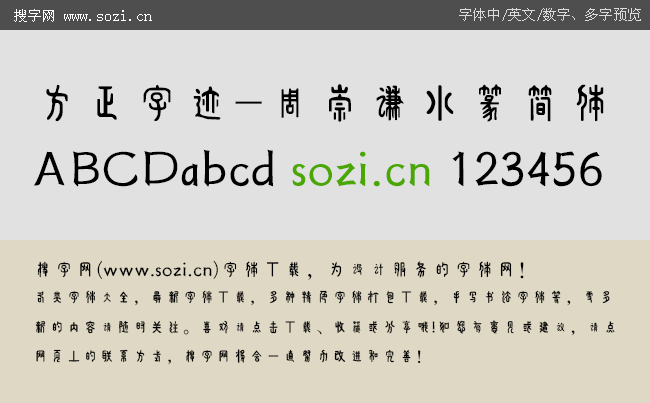
方正字跡-周崇謙小篆簡(jiǎn)體手機(jī)字體
搜字網(wǎng)給大家提供一款方正字跡-周崇謙小篆簡(jiǎn)體手機(jī)字體手機(jī)中文字體下載。這款手機(jī)字體字形規(guī)范,工整端莊;結(jié)構(gòu)嚴(yán)謹(jǐn),氣派大方;筆姿圓潤(rùn),線條流暢;粗細(xì)均勻,柔中有剛;用筆自如,心氣昂揚(yáng)。喜歡的朋友趕快下載吧。